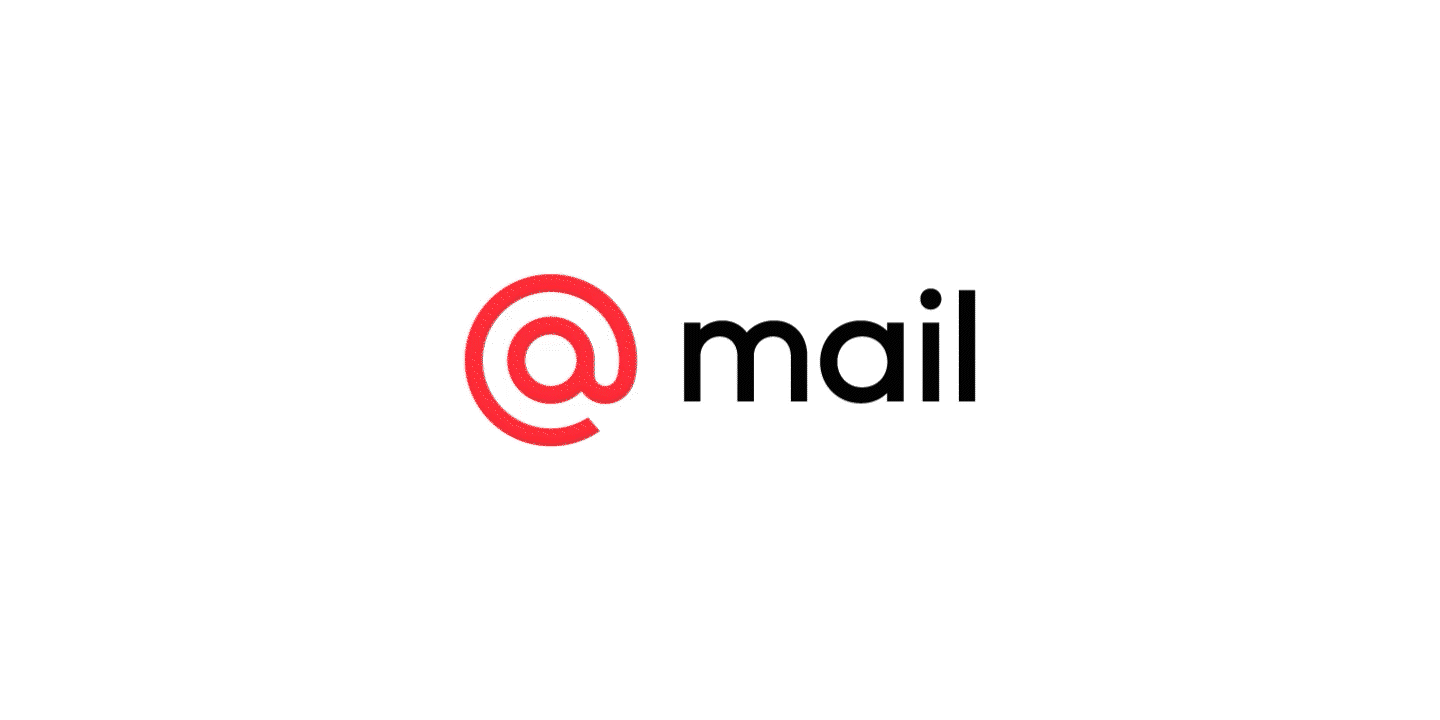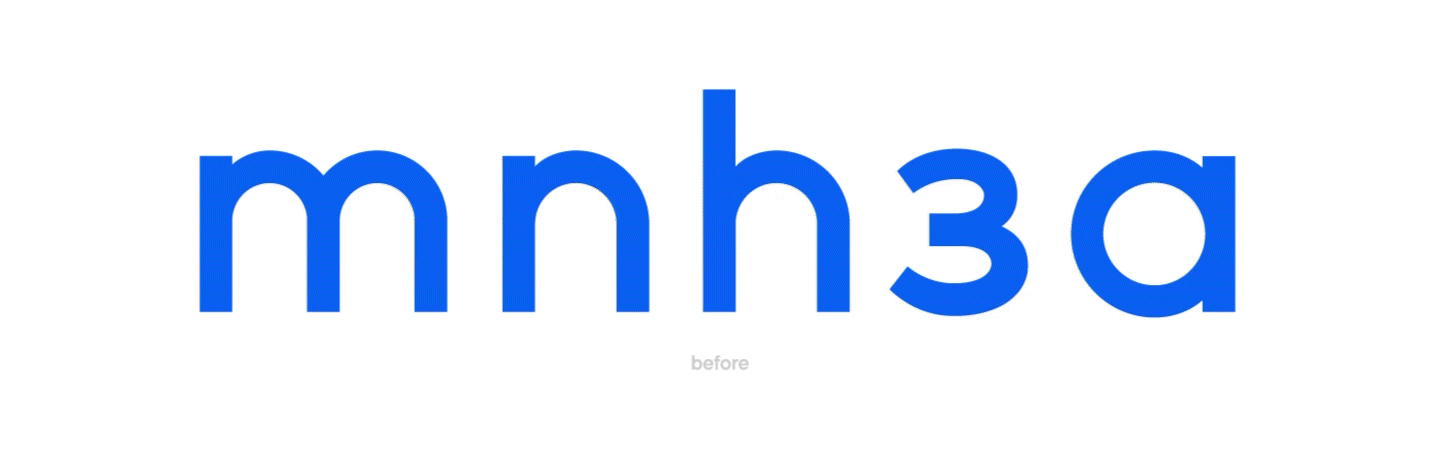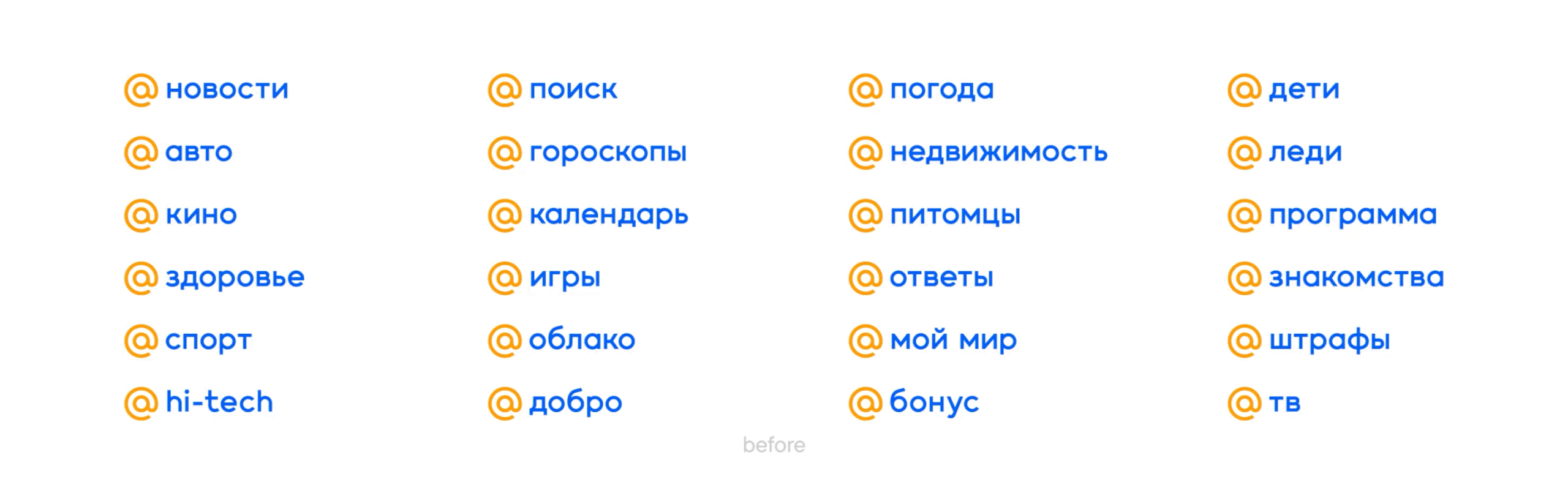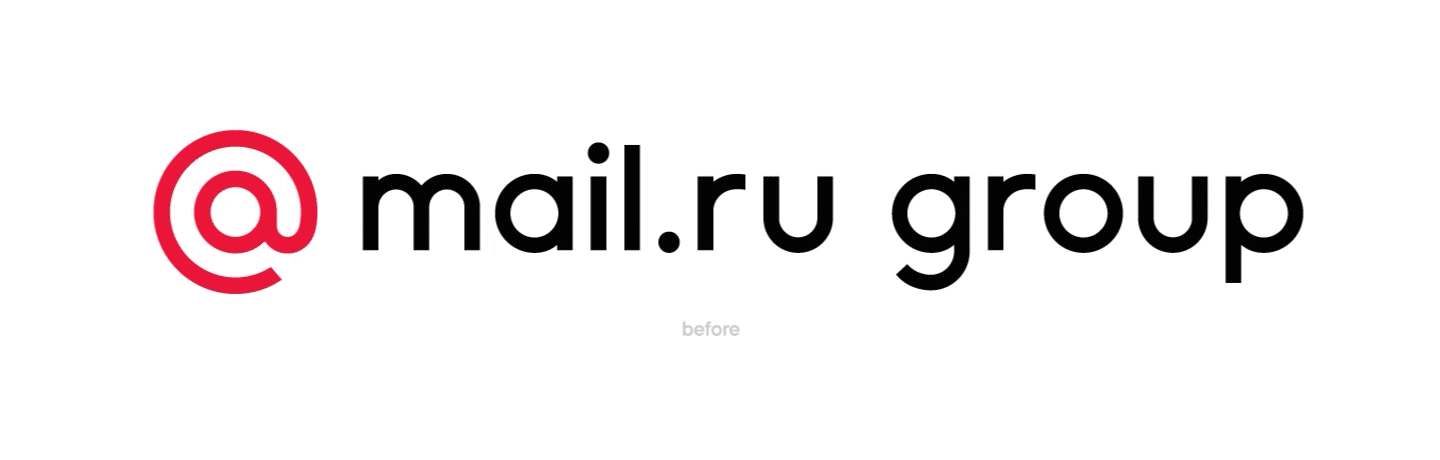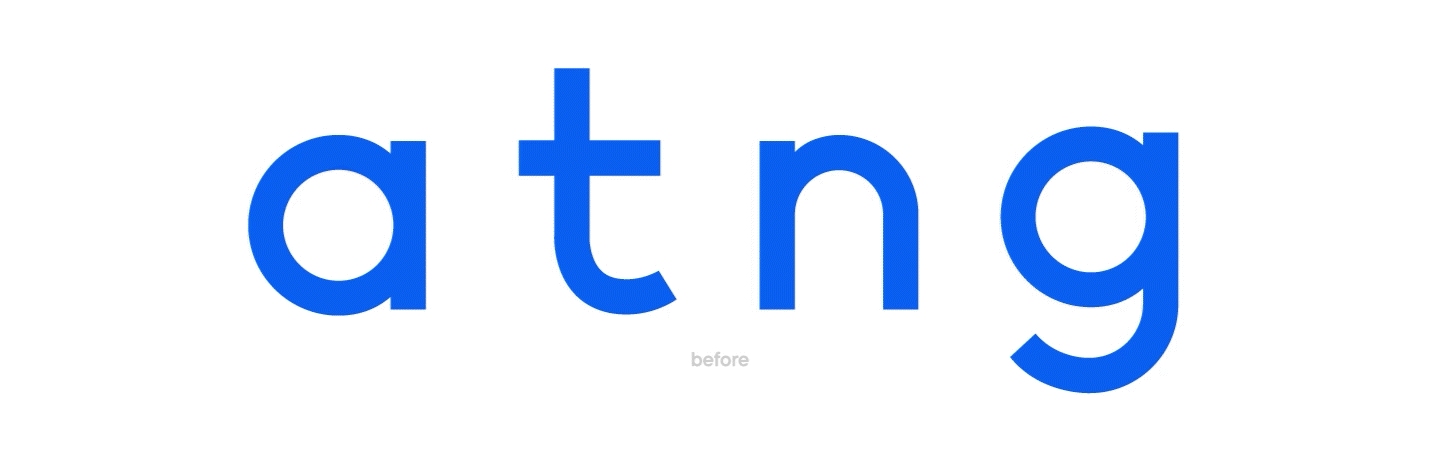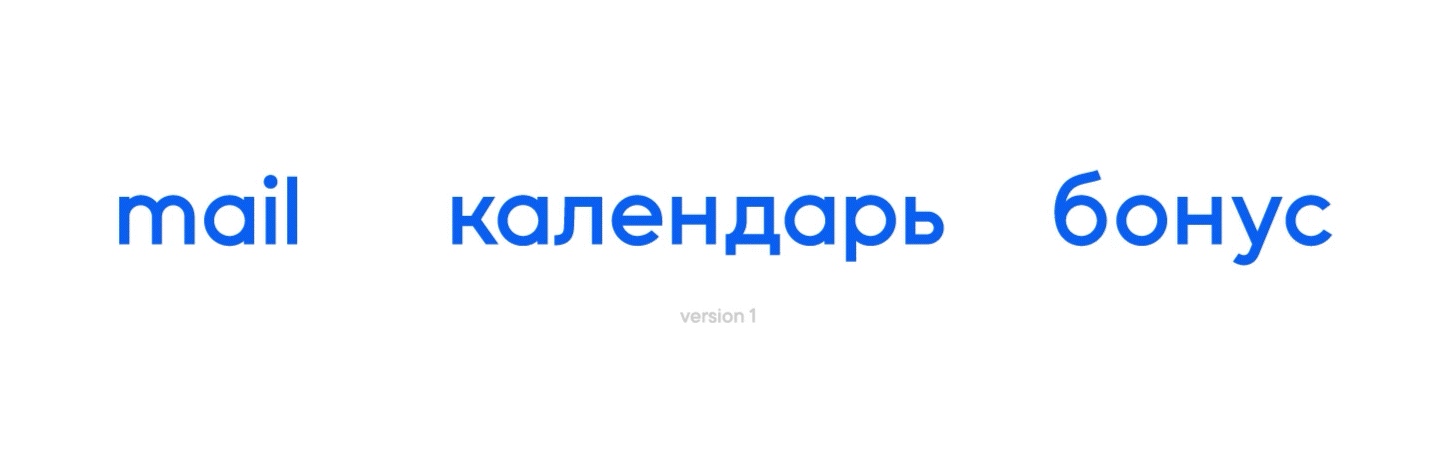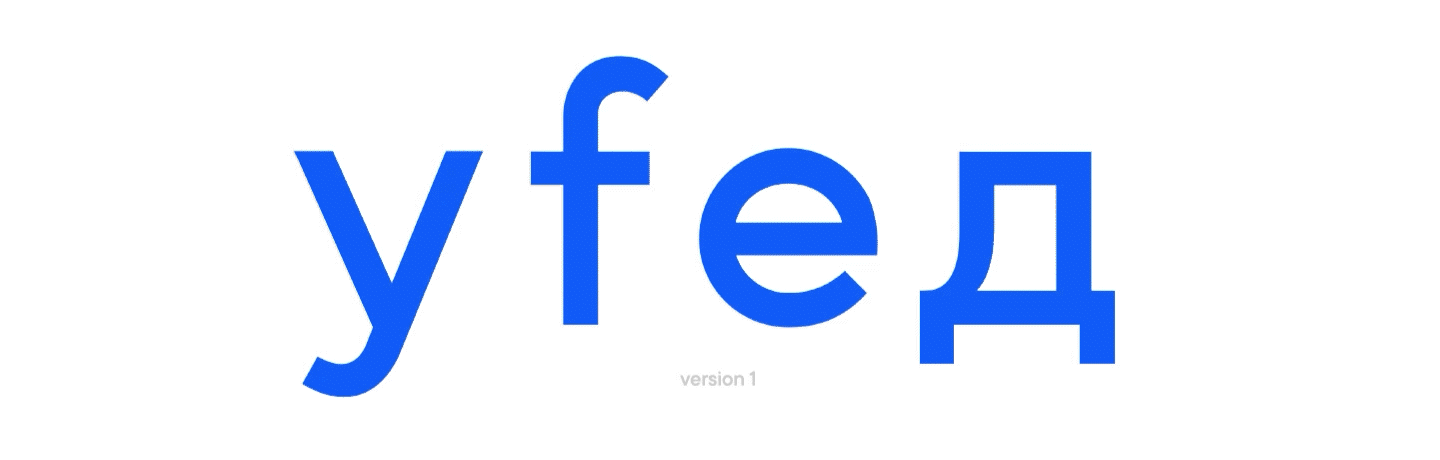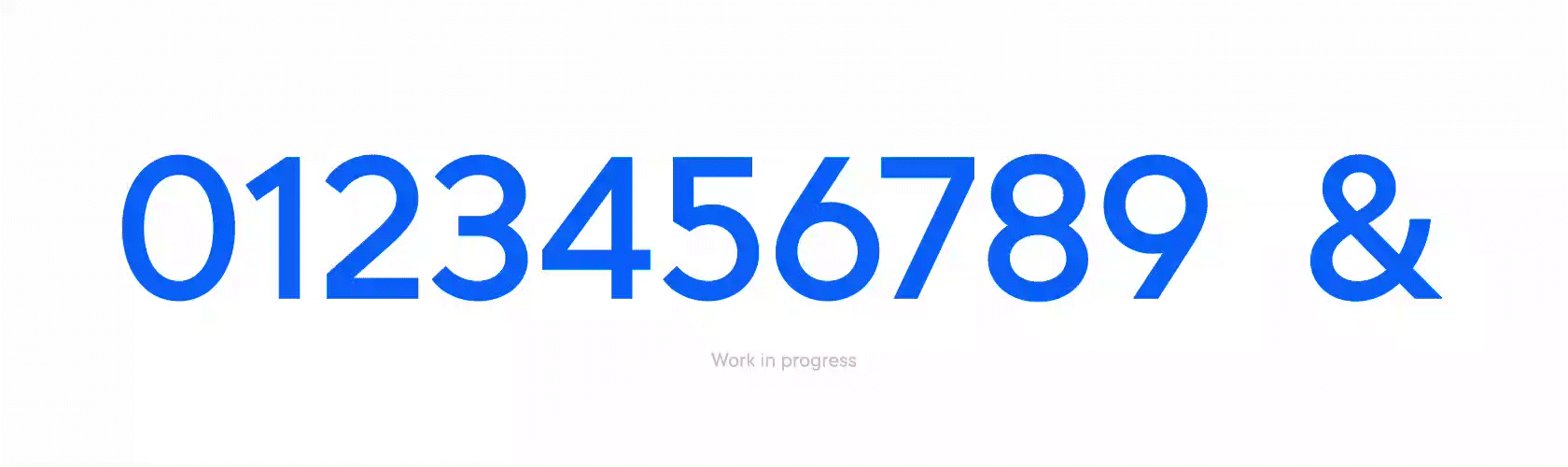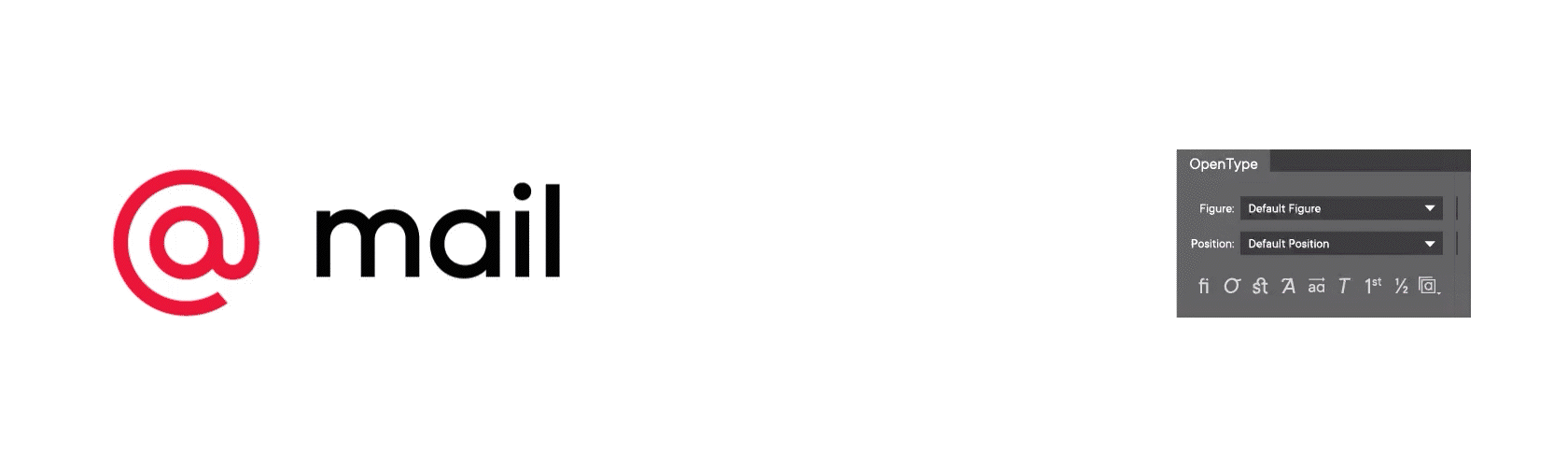
Создание шрифта для набора логотипов Mail.ru Group
Сегодня мы поделимся захватывающей историей создания шрифтовой гарнитуры для набора логотипов крупнейшего российского бренда. Вы увидите все этапы работы и чуть больше узнаете о том, как создаются шрифты.
Mail.ru Group
• Команда бренда Mail.ru Group, одна из самых крупных и известных IT-компаний в России. В экосистему VK, которую строит компания, входят социальные сети ВКонтакте и Одноклассники, онлайн-игры Warface, Crossfire и Armored Warfare, сервисы доставки еды, такси, платформы онлайн-образования, почта, мессенджеры и другие сервисы.
Пролог
Иногда в жизни компании появляется проект, который заставляет по-новому взглянуть на привычный формат работы. Бросает профессиональный вызов и преподносит полезный урок, в конце которого каждый получает опыт и приятные воспоминания.
Всё началось в августе 2018 года. К нам обратились Mail.ru Group. К тому моменту компания была на завершающем этапе масштабного ребрендинга. Они уже познакомили свою аудиторию с новым фирменным стилем, усовершенствованной концепцией и планами на будущие изменения. Осталось доработать шрифты для логотипов внутренних сервисов. Команда дизайнеров Mail.ru Group подготовила свою концепцию с желаемым характером шрифтовой гарнитуры, и изначально они пришли к нам для получения компетентных комментариев и технической подготовки шрифта. Задача выглядела простой.
Внутренние сервисы Mail.ru Group
Забегая вперёд, проект занял год, за который изначально предложенные Mail.ru Group буквы претерпели значительные изменения, в итоге став завершающим штрихом нового фирменного стиля бренда.
Часть первая. Начало
У нас был опыт в типографике и остро намётанный взгляд профессиональной команды на любые виды шрифтов. У Mail.ru Group — логотипы, которые они хотели трансформировать в удобный шрифт. Важный момент: в шрифт для набора логотипов, так как было необходимо масштабируемое решение, подходящее для разных названий проектов.
«О создании своей шрифтовой гарнитуры мы думали очень давно, с 2014 года. Полноценная работа над ребрендингом в 2019 году стала катализатором для этой идеи. Мы сделали большое исследование по редизайну логотипов в нашей сфере, которое показало устойчивый тренд к переходу от вычурных и ярких шрифтов с явным характером к нейтральным, светлым гротескам. Их легкость и ясность показались нам удобными для работы, ведь такой тип шрифтов хорошо читается на разных размерах и не отвлекает на себя много внимания»
Евгений Долгов, ведущий дизайнер бренд-команды Mail.ru Group
Наши лучшие умы и глаза схватили предоставленные буквы и начали их преображать. Исправлять то, что было неправильным с точки зрения типографики. Оттачивать выразительность каждой буквы. Превращать исходник в читаемый и гармоничный шрифт.
Первый подход к шрифту
Первый подход к шрифту
Mail.ru Group оценили наш порыв. Но в сложившейся ситуации крылось одно большое «но». Они представляли шрифт как продолжение своей концепции, и в логотипности шрифта для них крылось сакральное значение. Mail.ru Group видели свой шрифт как цельный брусок, монолитный и геометричный.
Для нас работа со шрифтом для логотипов в таком масштабе была новым опытом. Мы старались найти баланс между пожеланиями заказчика и своим видением, но профессиональная дотошность к деталям и следование правилам типографики иногда брали верх.
Тем не менее, в этот период произошло много изменений, получивших развитие в последующих этапах.
Этапы развития
• Изначально мы делали визуальные «влития-компенсаторы» в парадигме стандартного подхода, но в ходе обсуждений сделали их меньше. Овал стал визуально круглее, а шрифт — геометричнее.
• Уменьшили длину выносных элементов, чтобы шрифт выглядел монолитнее.
• Были эксперименты с высотой выносных элементов и букв j и g, наклоном диагоналей к, k и л.
• Ряд изменений коснулся пропорций букв, чтобы сделать шрифт более цельным.
«Мы хотели избежать тяжести жирных и темных начертаний в шрифте, особенно беря во внимание тот факт, что у Mail.ru Group проекты с разной длиной слов в названиях. Если короткие названия смотрелись хорошо в жирном начертании, то длинные выглядели не лучшим образом, особенно вблизи со светлым шрифтом в меню проекта. В итоге мы остановились на начертании Medium. Также, экспериментируя с анатомией букв, мы решили уменьшить у части знаков (таких как h t l g j b d) выносные элементы, что в итоге позволило получить более „сбитые“ и устойчивые логотипы»
Евгений Долгов, ведущий дизайнер бренд-команды Mail.ru Group
Мы много обсуждали, пробовали и искали. Меняли отдельные начертания, упорно отрабатывали детали букв. Находили точки соприкосновения, но никак не могли уловить общее видение.
Весь этот период был посвящён поиску взаимного понимания. Мелкими, но многочисленными изменениями каждый из участников выстраивал путь к той концепции, которую сложно было сформулировать в тот конкретный этап. Но которая, пока не осознаваемая участниками процесса, уже ожидала нас.